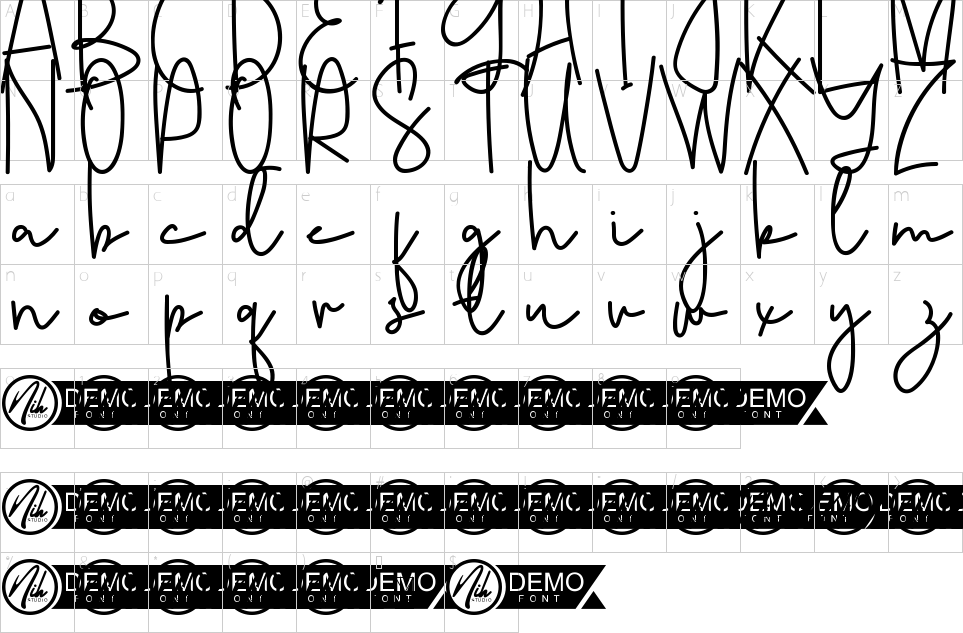
A fonte Sebuah Ilusi é uma criação da nihstudio disponível tanto para Windows quanto para Mac. Sebuah Ilusi é uma fonte elegante e versátil, ideal para diversas aplicações digitais. Esta fonte foi projetada com um toque de frescura e originalidade, combinando harmoniosamente com muitos estilos de design. A nihstudio, conhecida por produzir diversas fontes, não deixou de destacar o Sebuah Ilusi, que já foi baixada 242 vezes, mostrando seu valor e popularidade no mercado de fontes gráficas. Sebuah Ilusi é perfeita para aqueles que procuram uma fonte única e moderna para seus projetos.